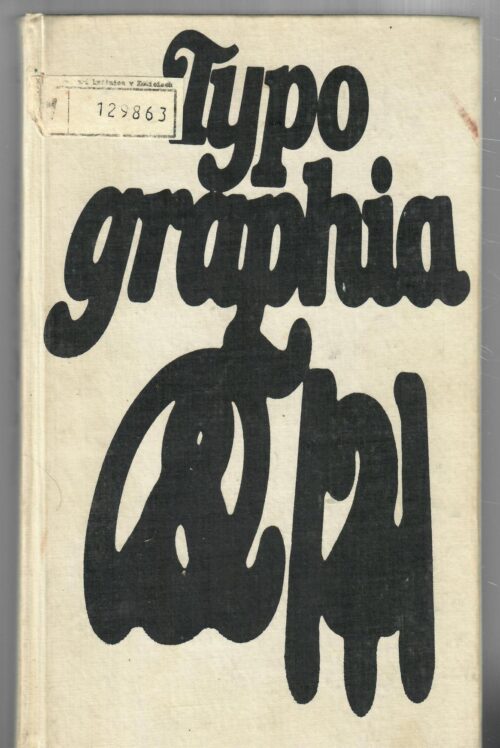
Kniha navazuje na publikaci Typographia – písmo, ilustrace, kniha, liší se však od ní jak náplní, tak vnitřní koncepcí. Vychází ze zhodnocení písem, ilustrací a knih klasické éry knihtisku, aby mohla analyzovat současnou situaci písma a tisku ve vztahu ke knize dneška a zítřka především z hlediska změn vyvolaných nahrazováním knihtisku fotosazbou. Jádrem knihy jsou ukázky písem, konfrontující klasické latinkové abecedy s novými abecedami, které vznikly pro potřebu fotosazby. Použití písem je ukázáno v návrzích typografického řešení grafických úprav knih a tisků, včetně ilustrací v různých typech publikací, s důrazem na volbu a rozvržení písma a ilustrace. Textová část pojednává též o problematice vztahu fotosazby k písmu, knize a ilustraci a o grafické úpravě publikací různého charakteru.